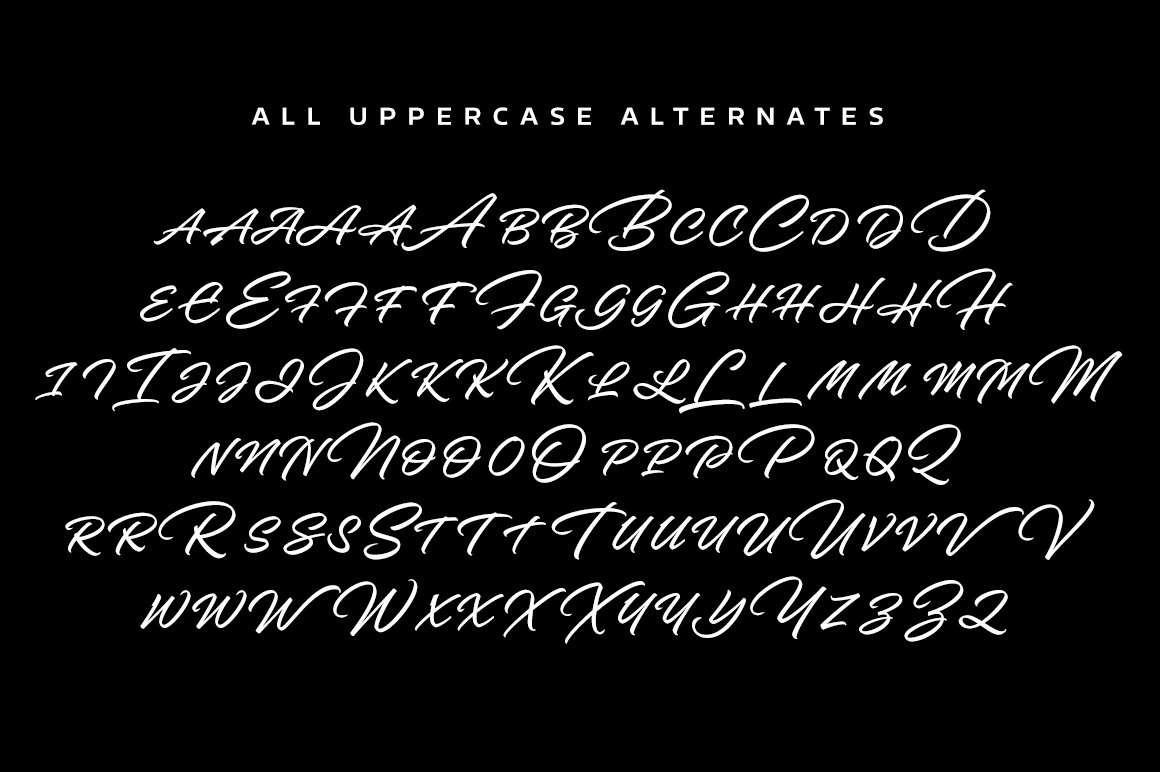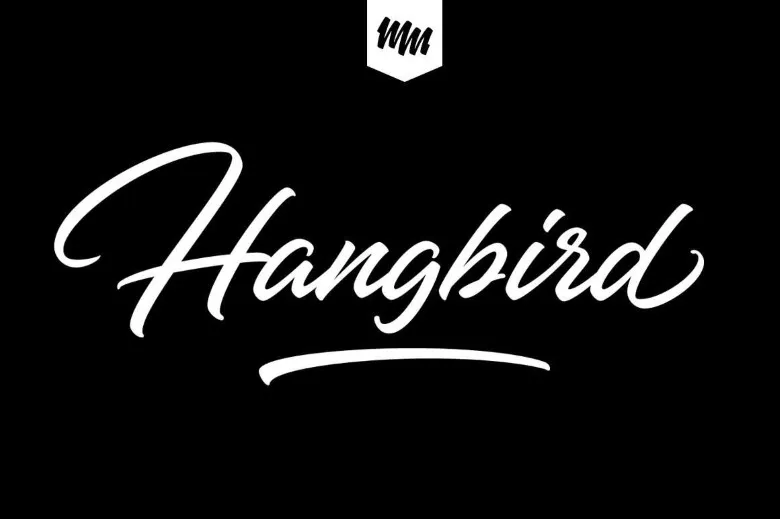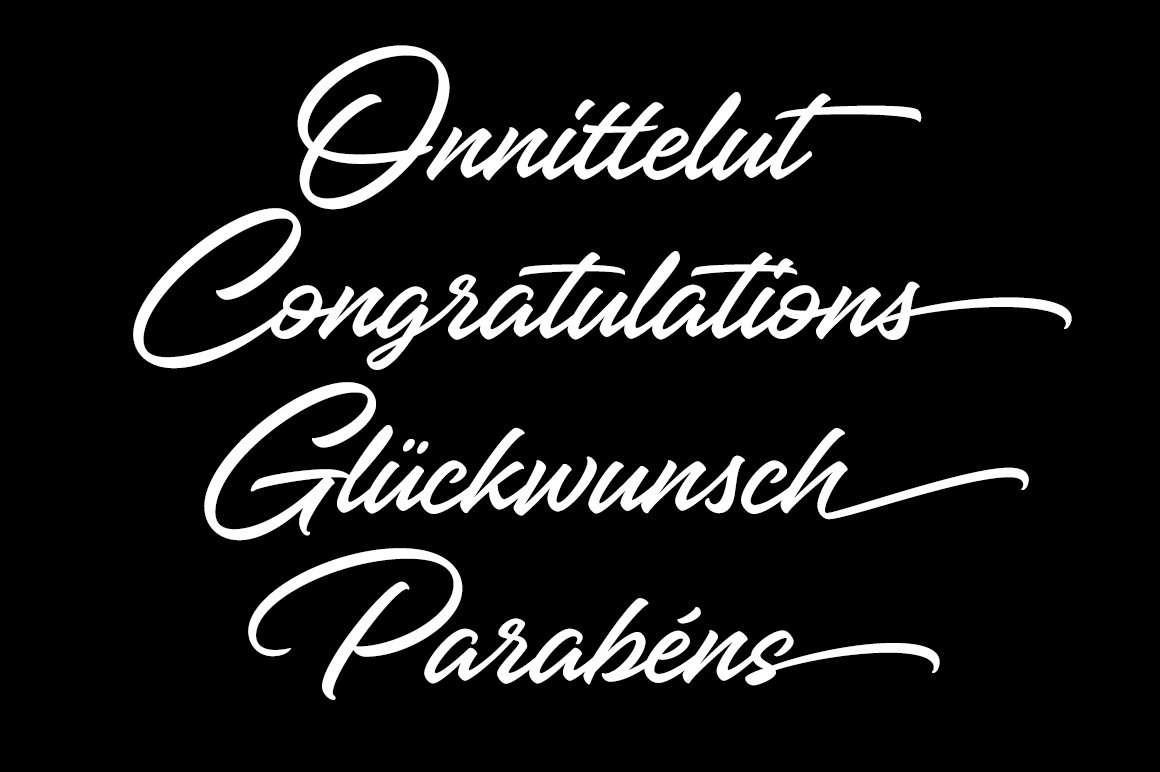
Font MTD Hangbird bị lỗi hiển thị ký tự “đ, ơ, ư” hoặc đường nét bo tròn bị vỡ hạt khiến sản phẩm bánh kẹo hay đồ chơi trở nên kém thu hút, làm giảm tính cạnh tranh.
Font MTD Hangbird là gì?
MTD Hangbird là phông chữ thuộc dòng Display Script mang phong cách vô cùng đáng yêu, thân thiện và đầy tính ngẫu hứng. Đặc trưng của Hangbird là các nét chữ tròn trịa, dày dặn và có độ uốn lượn linh hoạt, gợi nhắc đến nét chữ viết tay tinh nghịch trên bảng tin trường học.
Sức mạnh của font chữ MTD Hangbird là khả năng tạo hiệu ứng thị giác vui vẻ, giúp thương hiệu dễ dàng kết nối với cảm xúc khách hàng. Font MTD Hangbird việt hóa được xử lý kỹ lưỡng từng ký tự đặc thù tiếng Việt, đảm bảo dấu thanh nằm đúng vị trí và không làm hỏng cấu trúc bộ chữ.
Lưu ý: Với font Hangbird, bạn hãy tận dụng các bảng màu rực rỡ (vàng chanh, cam tươi, xanh cốm) để làm nổi bật nét chữ vui tươi, giúp bao bì sản phẩm thu hút hơn.
04 Ứng dụng font chữ MTD Hangbird việt hóa khi thiết kế và in ấn
Vẻ đáng yêu của font chữ MTD Hangbird giúp ấn phẩm trở nên sinh động và gần gũi:
- Thiết kế tem nhãn: Font chữ Hangbird cực kỳ phù hợp để in nhãn cho hũ bánh kẹo handmade nhờ phong cách vui nhộn và chân thực.
- Sản xuất hộp giấy: Chữ Hangbird in dập nổi trên hộp giấy Ivory tạo cảm giác hào hứng cho bé ngay khi nhận sản phẩm từ doanh nghiệp.
- In ấn đồng phục: Slogan dùng font Hangbird in chuyển nhiệt trên áo thun tạo vẻ ngoài dễ thương cho các bé trong hoạt động ngoại khóa.
- Trang trí túi giấy: Phông chữ này giúp bộ ấn phẩm học đường trở nên sinh động và bớt khô khan hơn trong mắt phụ huynh và học sinh.
Sử dụng font chữ MTD Hangbird cần lưu ý gì?
Để bản in sử dụng font chữ Hangbird đạt độ sắc sảo và thu hút, designer cần lưu ý:
- Kiểm tra hốc chữ khi in nhỏ: Hangbird có các hốc chữ nhỏ (như chữ “e”, “a”). Khi in tem nhãn siêu nhỏ, bạn nên nới rộng font một chút để tránh tình trạng mực bị lấp đầy khoảng trống.